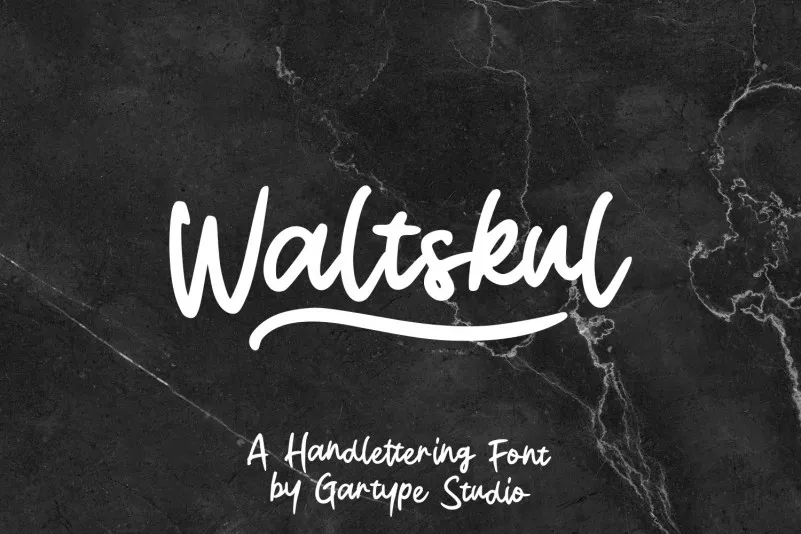
Waltskul Script Font – Download Grátis
A Waltskul Script é uma novidade de Gartype Studio, uma fonte escrita a mão que traz à tona um estilo divertido e versátil. Este script foi projetado para inspirar muitas idéias criativas, especialmente para designers atentos aos detalhes. Com alternativas e swashes para tornar seu projeto ainda mais atraente e sofisticada, a Waltskul é uma escolha ótima tanto para criações visuais simples como para projetos de nível maior. O destaque da fonte reside não apenas em sua beleza única, mas também na versatilidade. Compatível com múltiplos idiomas e adequado para diversos tipos de projetos como logomarcas, panfletos, flyers, cartazes, assinaturas, e mais, a Waltskul é uma fonte que se torna uma aliada indispensável em qualquer trabalho de design. Garanta sua versão agora, pois esta fonte não será disponível por muito tempo.